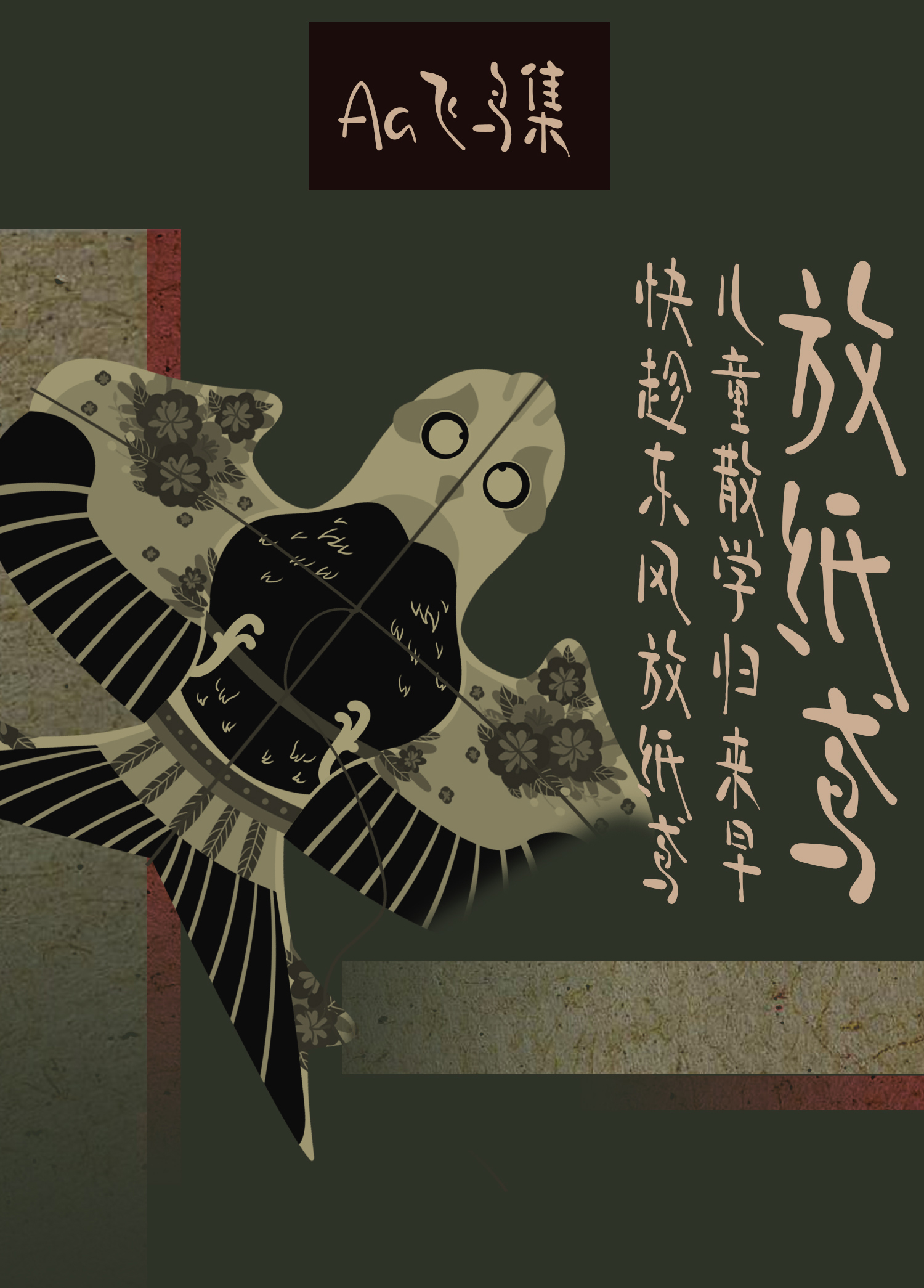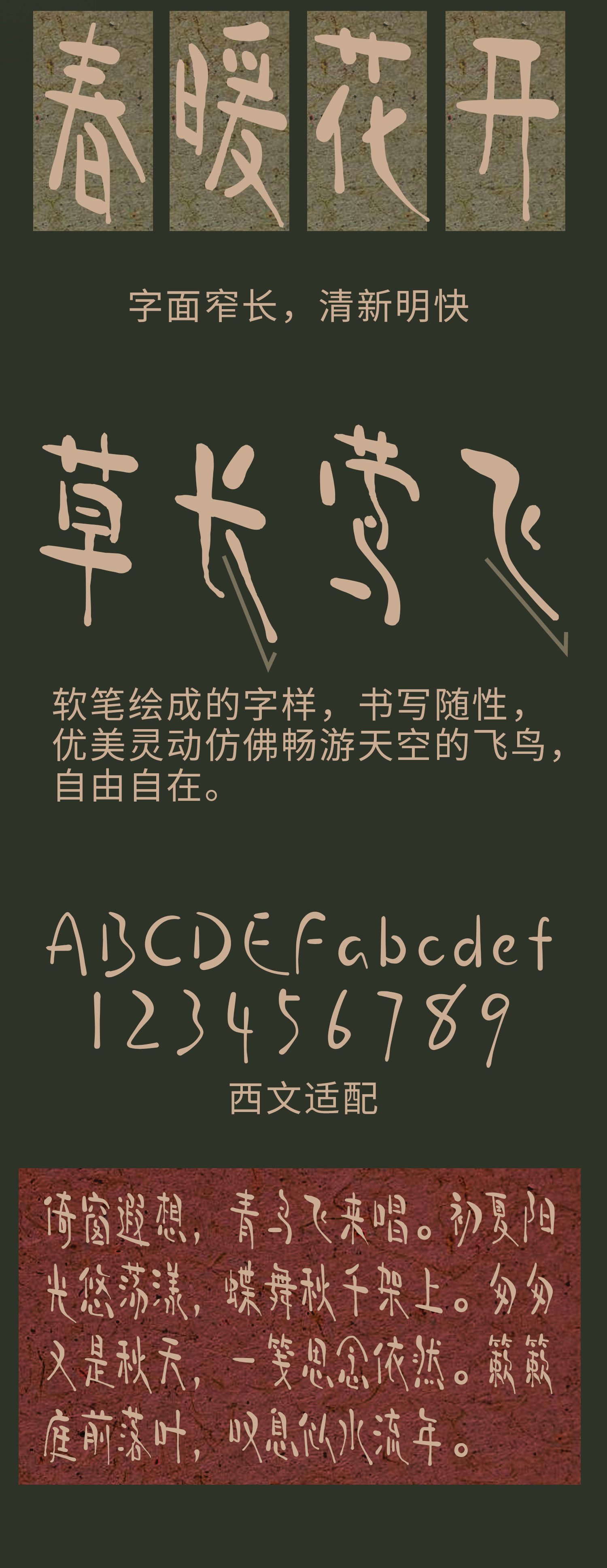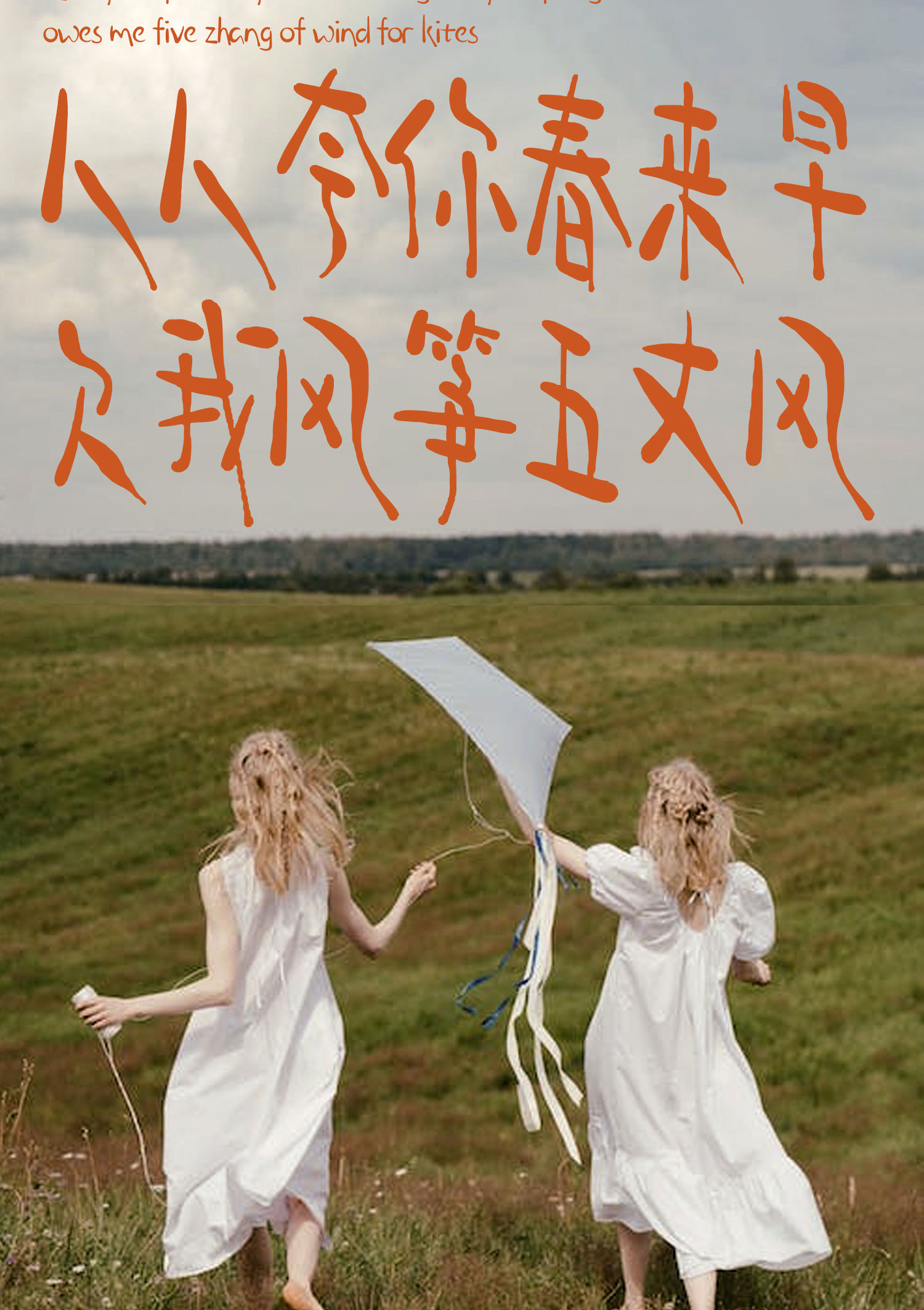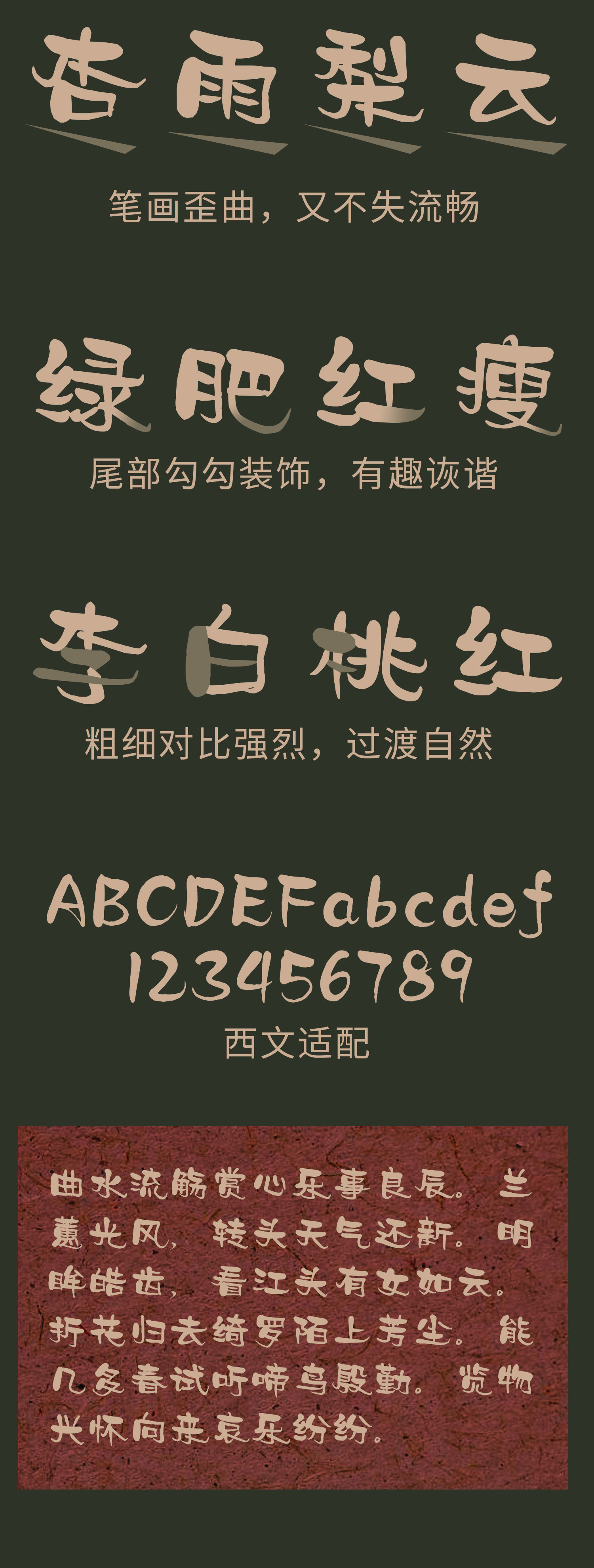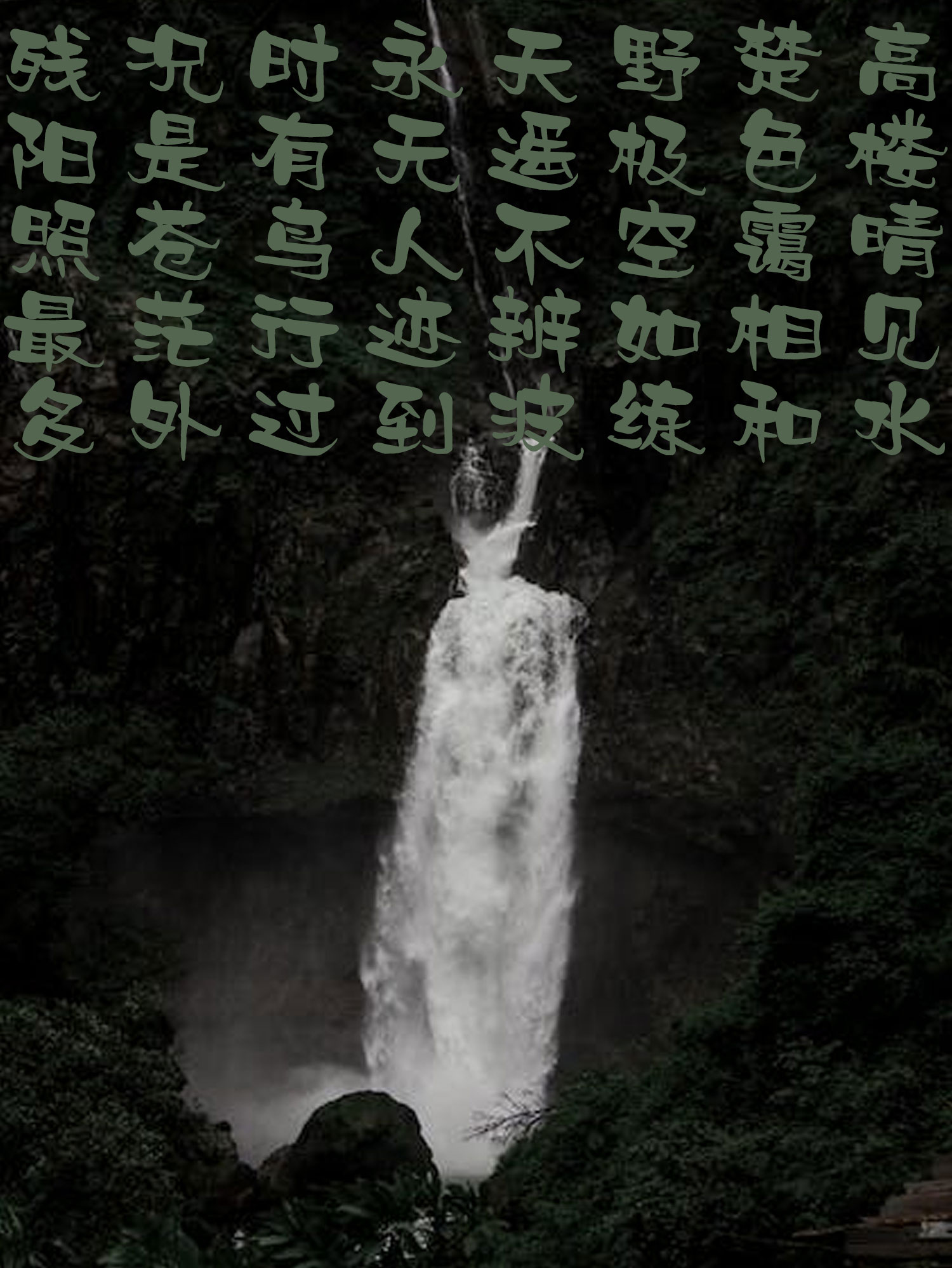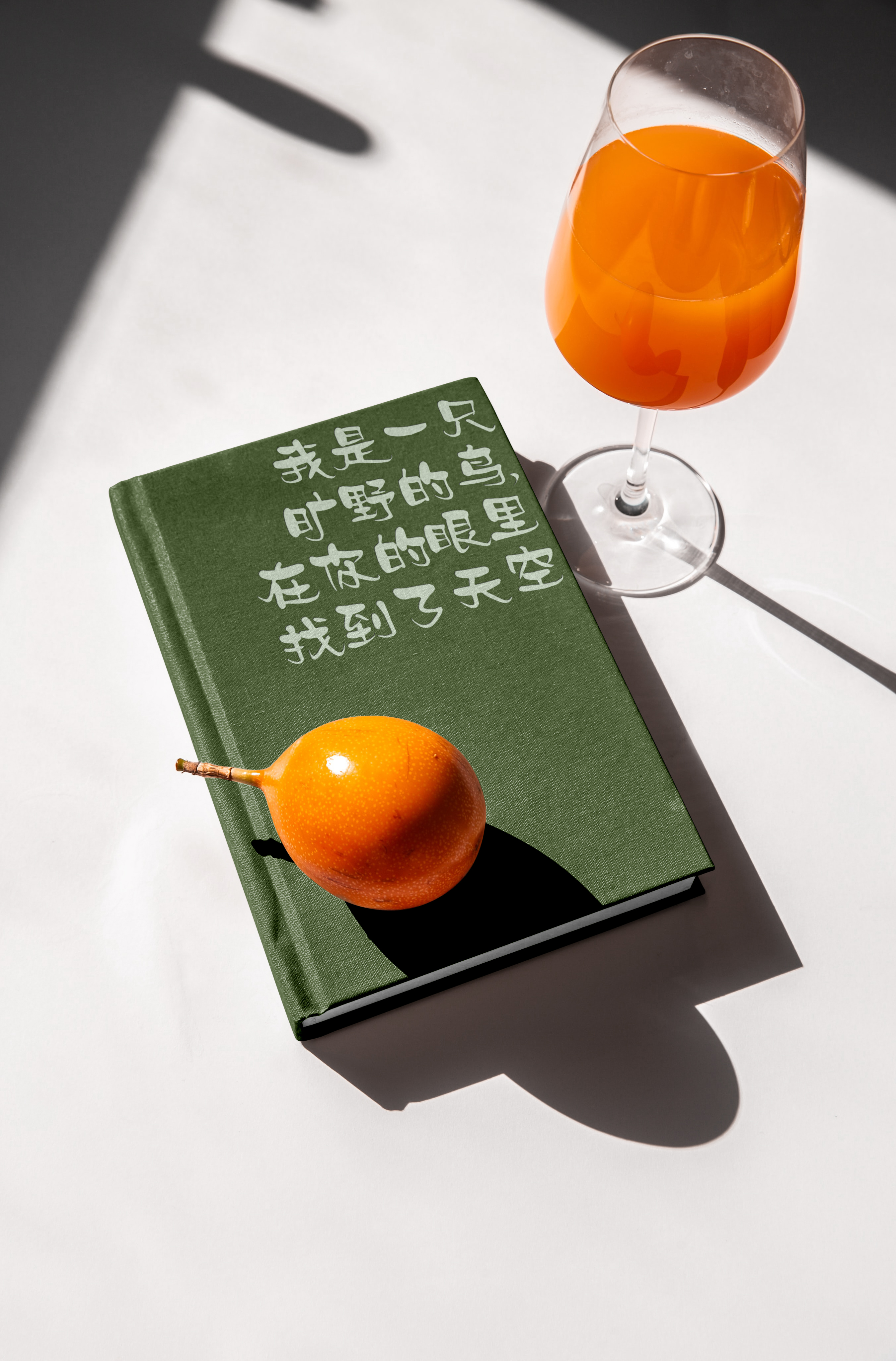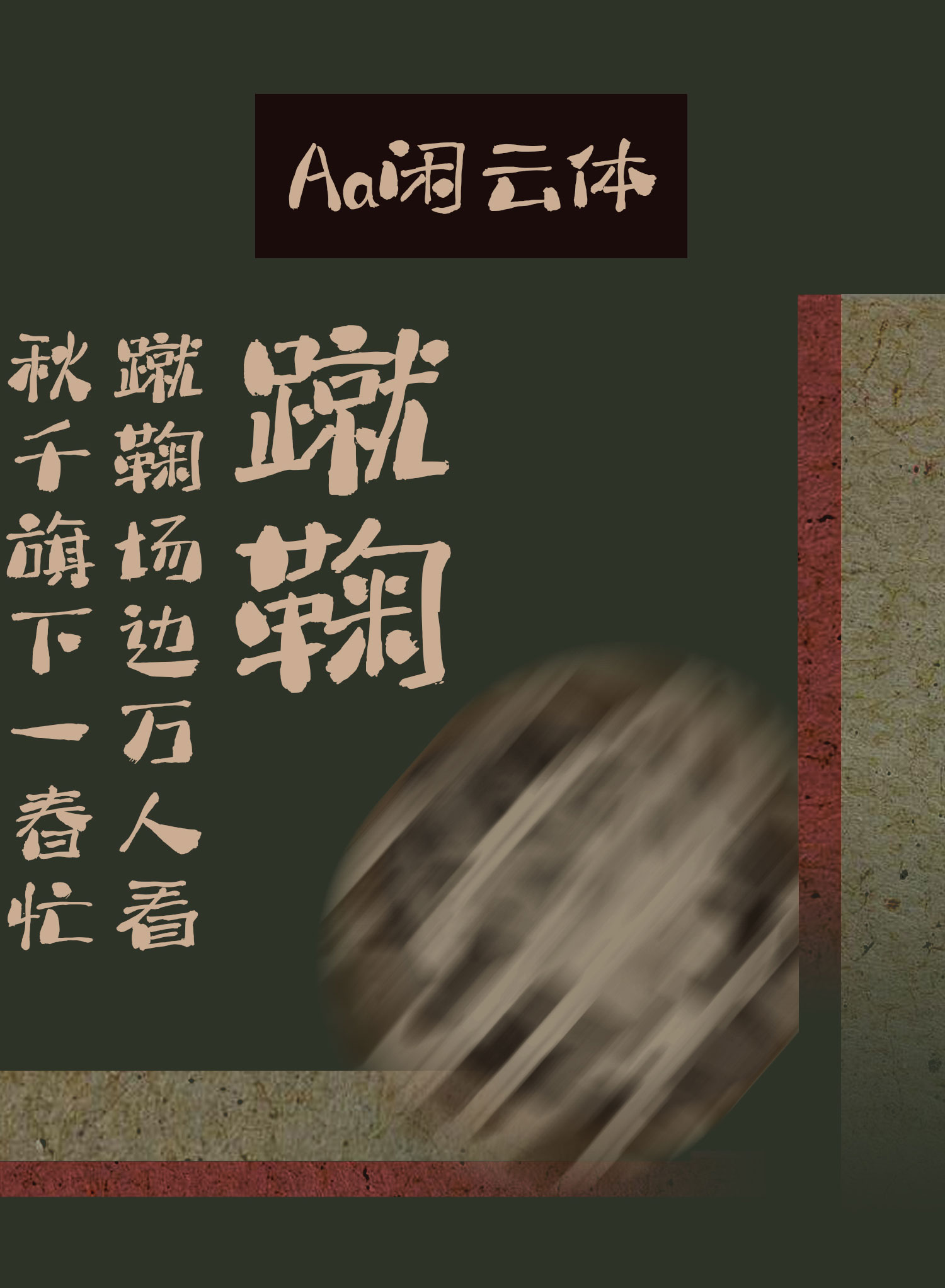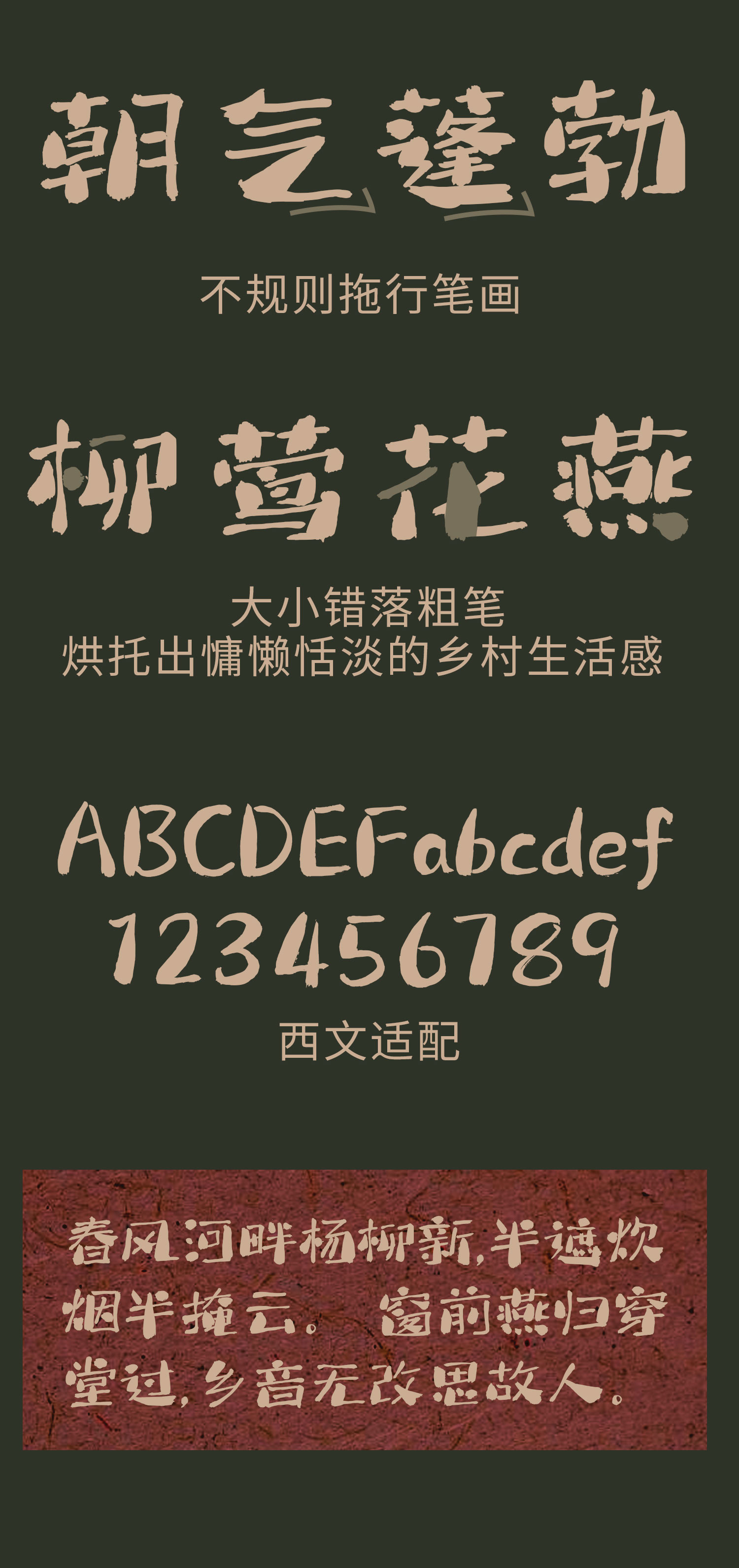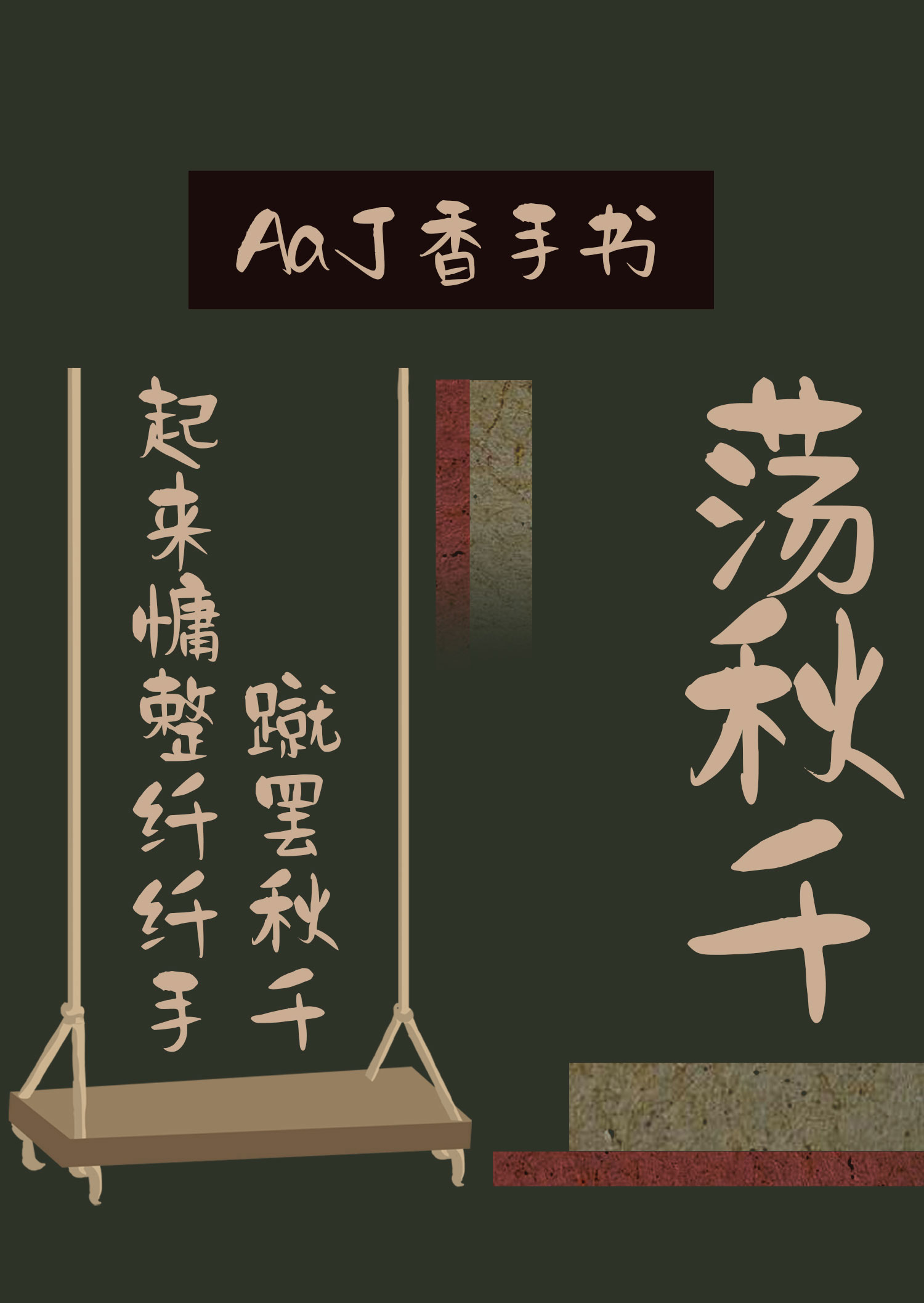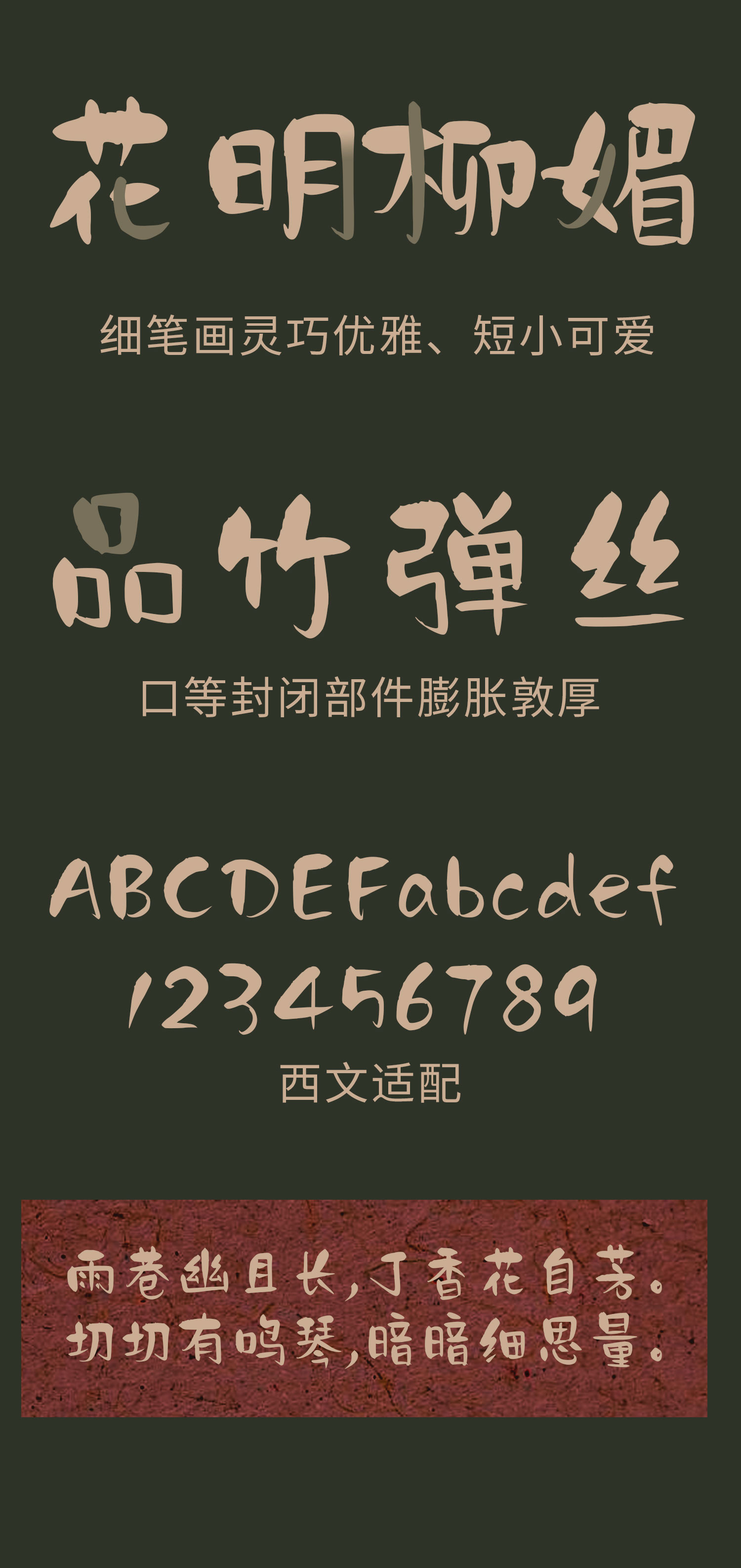
Aa字库春日字体推荐|古人游春图鉴
Aa字库春日字体推荐:
古人游春图鉴,当古人在谈论游春时,他们在谈论什么?
Aa飞鸟集
字面窄长,清新明快
软笔绘成的字样,书写随性,优美灵动仿佛畅游天空的飞鸟,自由自在
Aa汉乐府
笔画歪曲,又不失流畅
尾部勾勾装饰,有趣诙谐
粗细对比强烈,过渡自然
Aa闲云体
不规则拖行笔画
大小错落粗笔
烘托出慵懒恬淡的乡村生活感
Aa丁香手书
细笔画灵巧优雅、短小可爱
口等封闭部件膨胀敦厚